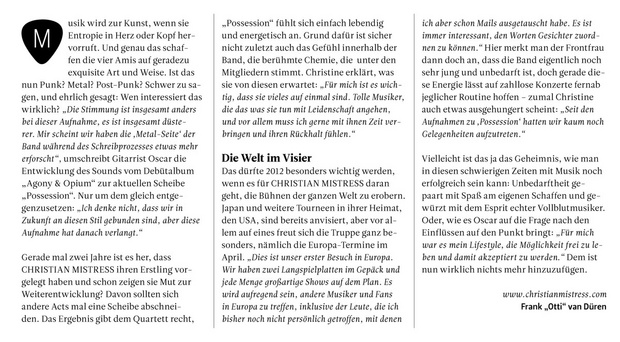
Doppelte Auszeichnung: Zitate im Massentext kursivieren?
ich brauche dringend Eure Meinung zu einem Problem, vor dass mich mein Auftraggeber erneut stellt.
Alle zwei Monate gestalte ich eine Zeitschrift mit 132 Seiten. Ca. 50% davon besteht aus reinem Massentext. In diesen Texten tauchen häufig Zitate auf, die durch Anführungszeichen kenntlich gemacht werden, aber auch Eigennamen von Musikgruppen, die in Kapitälchen stehen und Songtitel, die wiederum durch Anführungszeichen hervorgehoben sind.
Nun zu meinem Problem: Schon vor 6 Monaten, also drei Ausgaben, wollte man seitens des Verlags, dass alle Zitate in den Massentexten zusätzlich kursiv gesetzt werden, so wie es meine Vorgänger gemacht hatten. Ich habe damals darauf hingewiesen, dass eine doppelte Auszeichnug typografischer Unsinn ist und vor allem die Texte dann schrecklich aussehen, die zu knapp 3/4 aus Zitaten bestehen. Ich habe nach dieser Begründung dann erstmal ohne diese Kursivierung drei Ausgaben gelayoutet.
Nun kommt die Frage allerdings wieder, mit dem Hinweis, man hätte sich mit allen Autoren beraten und sei nun der Meinung, dass die Texte so nicht gut lesbar wären und man sich wieder eine Kursivierung wünscht, auch wenn die Texte dann wirr erscheinen.
Was meint Ihr? Einfach machen, weil der Kunde es so will? Gibt es weitere gute Argumente gegen eine doppelte Auszeichnung? Es sträubt mich wirklich bei dem Gedanken an ein Mischmasch aus normalem kursiven Text ...
In der Frage der doppelten Auszeichnung wäre mein Urteil eindeutig: Unsinn! Entweder Zitate durch Anführungszeichen kenntlich machen oder durch Kursivsetzung, nicht beides.
In der Frage, ob es sinnvoll ist, Zitate kursiv zu setzen, bin ich unentschieden. Die einzige mir bekannte Reihe, die Kursivsetzung praktiziert, sind die rororo-Biographien (offensichtlich auch in neuen Ausgaben, wie man hier z.B. sieht: http://www.monographien.de/fm/131/Rathjen_Beckett_Samuel.pdf). Ich finde das persönlich schlecht zu lesen: bei einzelnen Wörtern, weil ich mich frage, ob das jetzt eine Hervorhebung im Text ist oder ein Zitat; bei längeren Passagen, weil die Kursive einfach schlechter lesbar ist.
Auf der anderen Seite haben lange Zitate, die "nur" durch Anführungszeichen gekennzeichnet sind, den Nachteil, dass man den Überblick verlieren kann, was Zitat ist und was "normaler" Text. In Büchern finde ich es hilfreich, wenn lange Zitate typografisch vom Rest abgesetzt sind. In Deinem Fall ist das aber wohl keine Alternative. Vielleicht hängt mein Urteil davon ab, welche Schrift verwendet wird und wie gut die Kursive lesbar ist. Ich tendiere aber eher zur Variante mit Anführungszeichen (hoffe aber, dass noch kreative Alternativen vorgeschlagen werden).
Könntest Du mal eine Beispielseite einstellen, notfalls mit Blindtext?
es kommt auf den text an. du schreibst es werden viele eigennamen und songtitel
verwendet die ebenfalls mit anführungszeichen gesetzt werden ...
dann würde ich die zitate zusätzlich kursiv setzten einfach um es lebarer zu halten.
für die songtitel, also auszeichnung in auszeichnung würde ich dann die ‚einfache‘
anführung verwenden.
man könnte auch an dem tonwert der zitate arbeiten, also nicht kursiv sondern
in 80 % schwarz oder ein blaugrau bzw. eine zum design passende farbe.
Anbei ein Beispiel, wie ein halbseitiger Text mit kursivierten Zitaten ausehen würde (darüber steht auf der Seite noch ein Bild, Headline, etc) und hier Link zu einer größeren Version (die hochgeladene Grafik wurde herunterskaliert, wie ich eben gesehen habe): Schrifttest
Das Argument, kursive Zitate würden die Unterscheidbarkeit von Zitaten und Songtiteln unterstützen, ist natürlich gut! Mit unterschiedlichen Schriftfarben würde ich ungern arbeiten, da die Texte oft auf einem farbigen Untergrund (z.B. Fotos) stehen und ich dann keine Einheitlichkeit über die 132 Seiten erreichen kann. Natürlich könnte man die Zitate auch in der Sans der Schriftfamilie setzen. Oder eben die Songtitel, was noch mehr Sinn machen würde.
Was meint Ihr? Ist der Text im Beispiel schrecklich genug, um die Kursivierung nicht zu machen, oder geht es sogar?
Hier hält sich ja die Zitatlänge immer noch in Grenzen. Sollte es aber tatsächlich Zitate über mehrere Spalten geben, macht eine kenntlichere Auszeichnung, als die der bloßen Anführungszeichen (wie Liuscorne schon beschrieben) wirklich Sinn.
Die Kursive jedoch liest sich in der Tat schwer. Für meine Begriffe liegt das aber nicht an der Kursivstellung an sich, sondern an der sehr eng laufenden Kursive dieser Schrift. (Welche ist das eigentlich? Schönes g!)
Du sagtest, hier wäre auch noch eine Sans im Angebot? Könntest Du Dir vorstellen, die mit ins Boot zu holen? Auf alle Fälle wäre zum Vergleich eine Alternative mit Sans-Zitaten (regular) hilfreich.
Wenn mein Kunde also meint, es ergäbe sich momentan eine "Bleiwüste", sollte dann nicht im Lektorat mit mehr Absätzen und Zwischenüberschriften gearbeitet werden?
Mir gefällt die Leitura-Kursive gar nicht: Alles wackelt hin und her, und die Zurichtung ist einfach schlecht. (Die Leitura News Italic ist etwas besser.)
Danke für den Hinweis! Die "Leitura News Italic 1" könnte genau die Lösung sein!